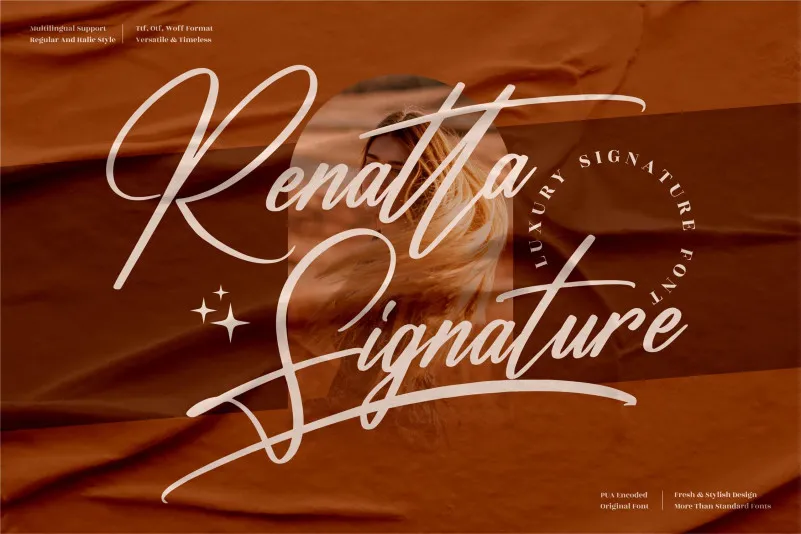
Renatta Signature Font – Download Grátis
A Renatta Signature Font é a escolha perfeita para projetos exclusivos que buscam uma assinatura única e sofisticada. Sua natureza elegante combina com diversos formatos de criação, incluindo logomarcas, projetos de marca, designs de móveis de casa, embalagens de produtos, tigelas, cartões de mensagens, convites de festa, carteirinhas de nome e todas as outras opções que exigem um toque de luxo. Inspirada em texturas fluidas e harmoniosas, essa fonte idealiza o pensamento criativo, adicionando uma personalidade autêntica aos seus projetos finais. Adaptável para uma variedade imensa de aplicações, a Renatta Signature é uma fonte perfeita para quem busca um toque único e sofisticado em todos os tipos de projetos.